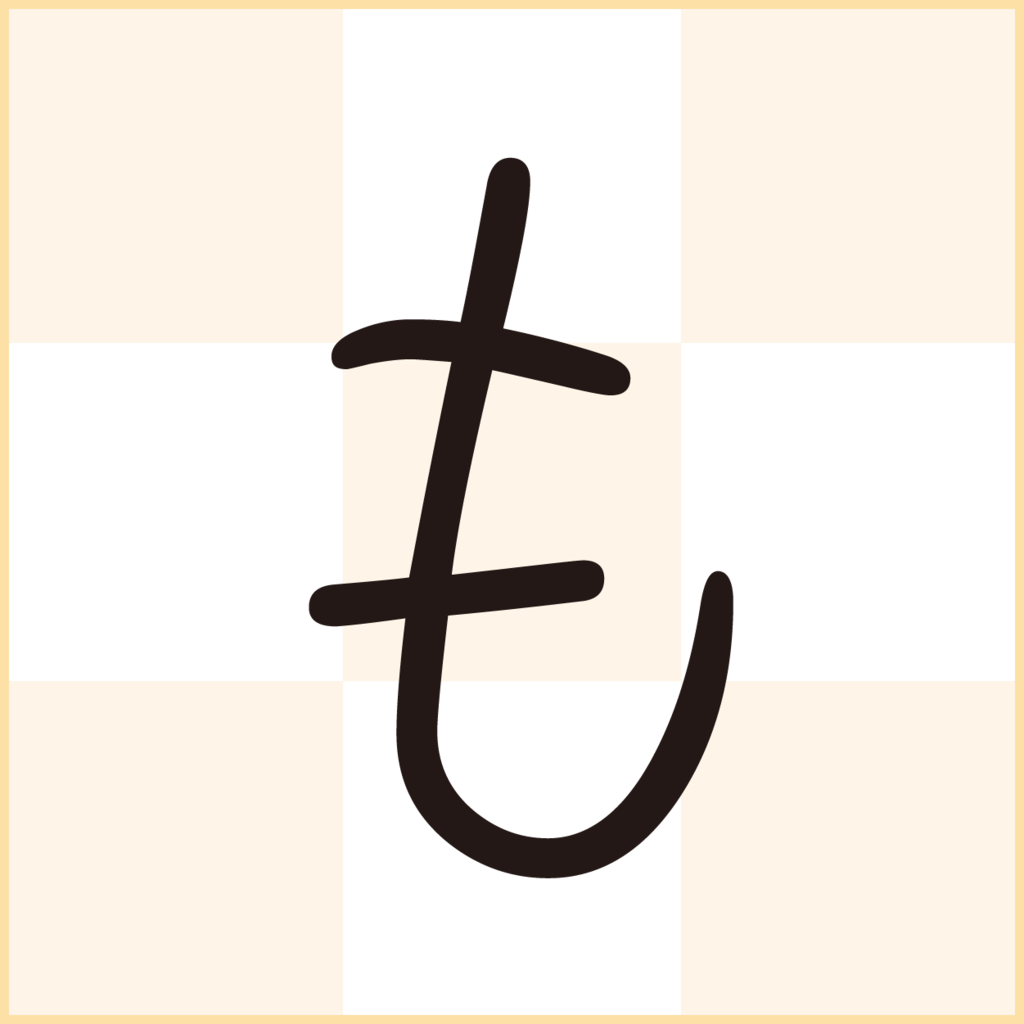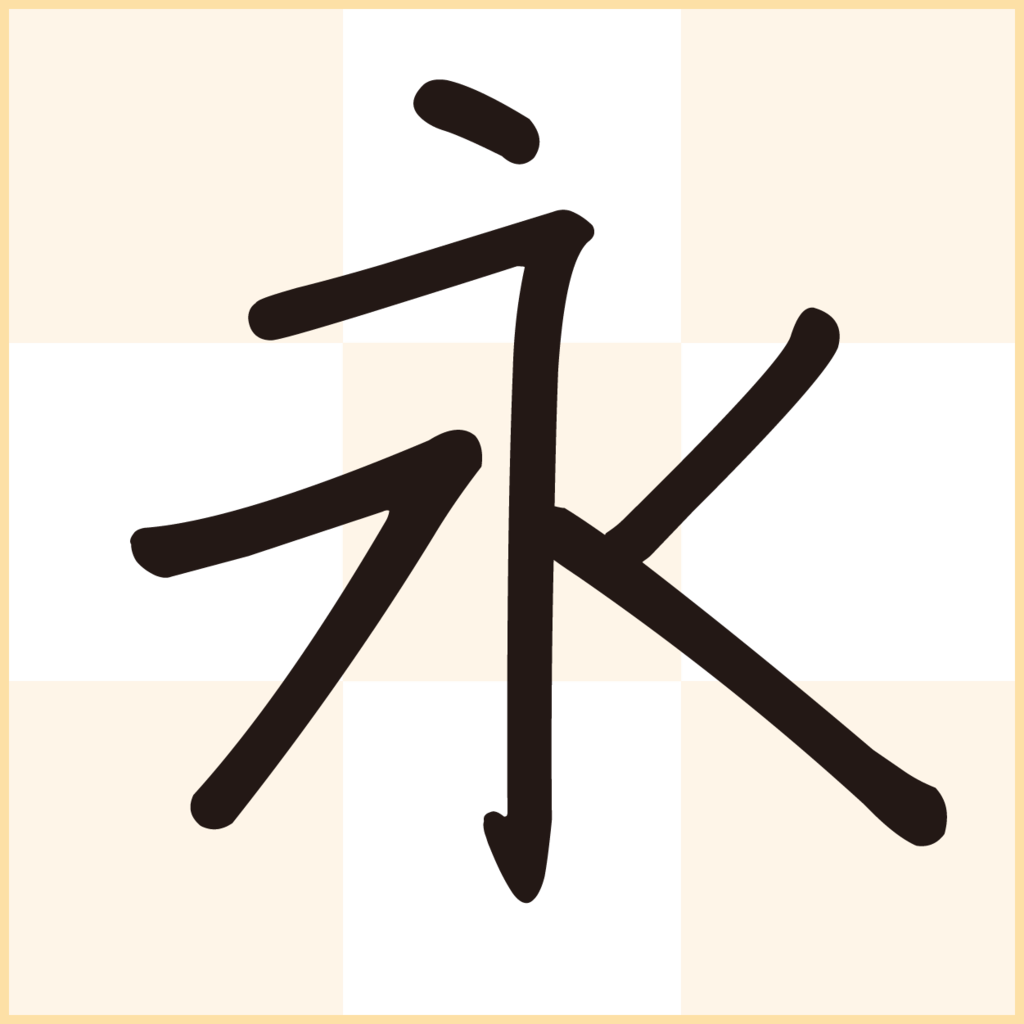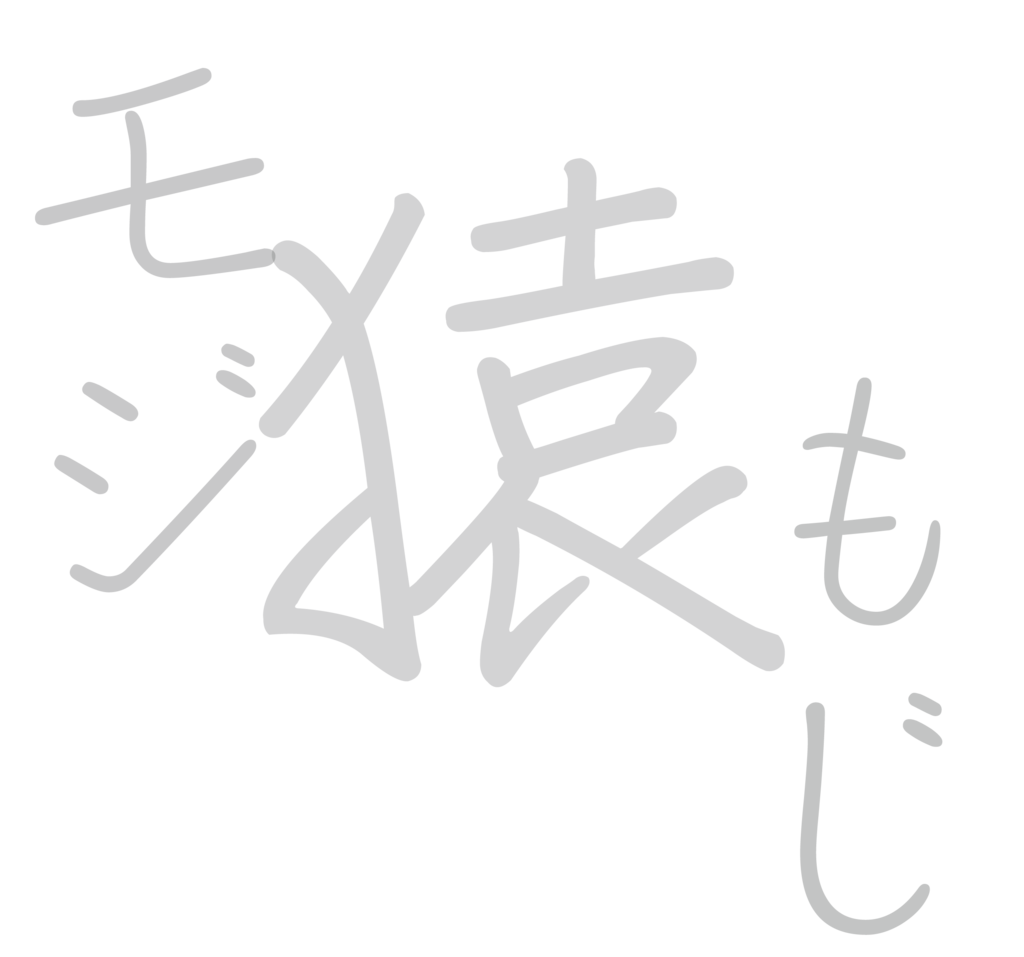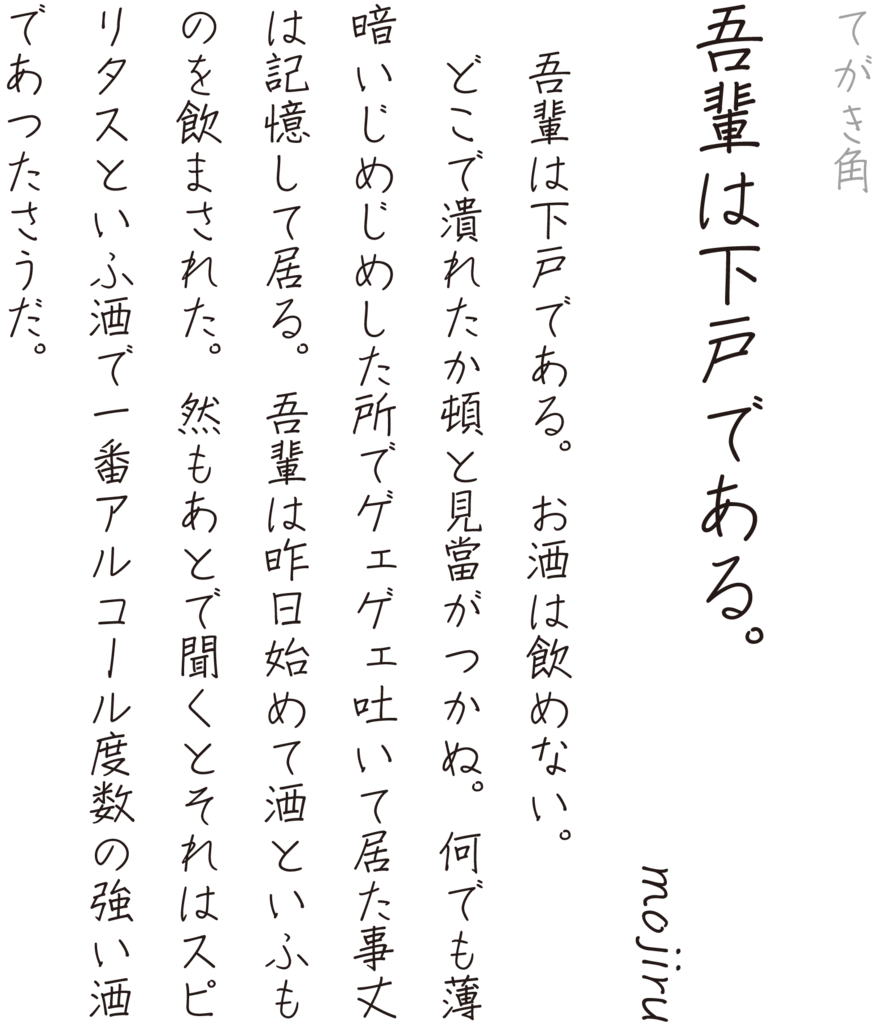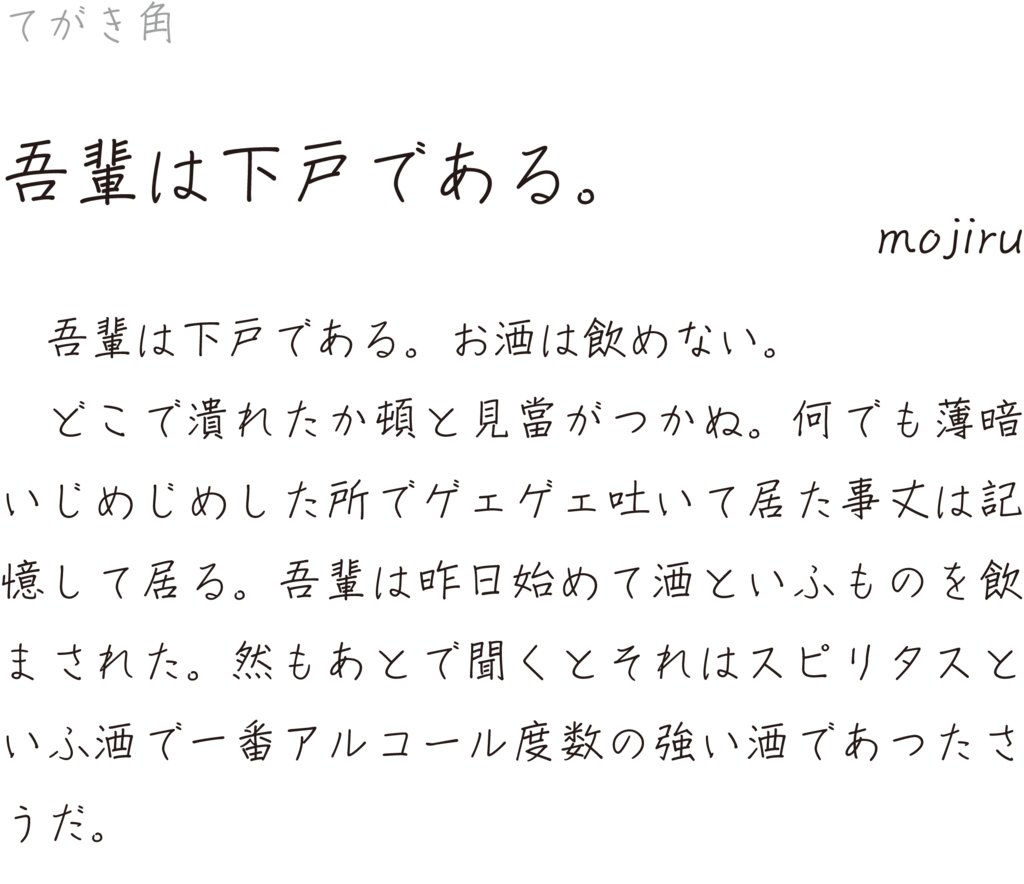
てがき角
「てがき角」は、0.7mmのボールペンを使用して芯の強いデザインをイメージした書体。字幅が広く、引き締まったラインで横画、縦画、左払い、右払いにメリハリを利かせており、書体に自然な貫禄を感じることができる。また、可読性が失われないように配慮しつつ、自然な手書き文字を再現している。しおり、小説、詩集、招待状からグラフィックデザインまで幅広い用途で使用できる。